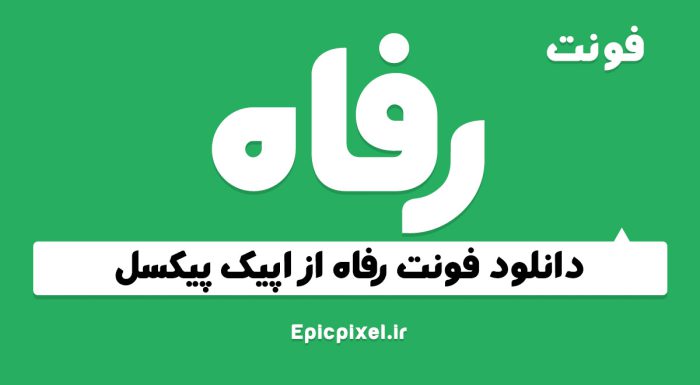
5 فونت رفاه فارسی
| ⭐ توضیحات | مجموعه ای کامل از فونت های رفاه و نسخه شبیه سازی شده بنام اپیک رفاه دانلود فونت اپیک رفاه با پشتیبانی از حروف فارسی / انگلیسی (لاتین) ، اعداد فارسی Fu Num و انگلیسی بهمراه نسخه وب |
فونت بانک رفاه یک فونت دکوراتیو برای طراحی لوگوتایپ و متن های طولانی
مقدمه
فونت رفاه یک فونت دکوراتیو است که برای طراحی لوگوتایپ و متن های طولانی مناسب است. این فونت توسط یک طراح حرفه ای و با سابقه فونت فارسی، طراحی شده است. فونت رفاه در سال 1402 به بازار عرضه شد و با استقبال خوب کاربران روبرو شد. این فونت دارای ویژگی های منحصر به فرد و جذابی است که در ادامه به آنها خواهیم پرداخت.
تعریف و معرفی فونت رفاه
فونت رفاه یک فونت دکوراتیو است که بر اساس الگوهای هندسی و ساده ساخته شده است. این فونت دارای حروف بزرگ و کوچک، اعداد، علائم نگارشی و نمادهای خاص است. این فونت با تمام قلم های لاتین سازگار است و می توان از آن برای نگارش متن های چند زبانه استفاده کرد. فونت رفاه برای طراحی لوگوتایپ، پلاکارد، بروشور، پوستر، کارت ویزیت، سربرگ، بنر، تقویم، سررسید و متن های آموزشی، هنری و تفریحی مناسب است.
اهداف و مزایای استفاده از فونت رفاه
اولین هدف ایجاد یک فونت دکوراتیو با کیفیت بالا و قیمت مناسب برای کاربران ایرانی و عربی است. دومین هدف ارائه یک فونت با ساختار و ترکیب حروف منحصر به فرد و جذاب است که برای طراحی لوگوتایپ و متن های طولانی مناسب باشد. سومین هدف پشتیبانی از سه زبان فارسی، عربی و انگلیسی با حروف لاتین سازگار است. چهارمین هدف دسته بندی و حالات مختلف فونت رفاه است که شامل نرمال، نرمال ایرانیک، بولد و ضخیم می باشد. پنجمین هدف سهولت استفاده از فونت رفاه در برنامه های مختلف است.
دانلوداستفاده از فونت رفاه چندین مزیت دارد. اولین مزیت زیبایی و جذابیت فونت رفاه است که باعث می شود مخاطب را به خود جذب کند. دومین مزیت خوانایی و روان بودن فونت رفاه است که باعث می شود مطالب را به راحتی بخوانید و درک کنید. سومین مزیت چند منظوره بودن فونت رفاه است که باعث می شود برای هر نوع طراحی و نگارش متن مناسب باشد. چهارمین مزیت چند زبانه بودن فونت رفاه است که باعث می شود برای نگارش متن های چند زبانه بدون نگرانی از تغییر قلم استفاده کنید.
ویژگی های فونت رفاه
در این بخش به بررسی ویژگی های فونت رفاه خواهیم پرداخت. این ویژگی ها شامل نحوه استفاده از فونت رفاه در برنامه های مختلف، ساختار و ترکیب حروف فونت رفاه، پشتیبانی از سه زبان فارسی، عربی و انگلیسی و دسته بندی و حالات مختلف فونت رفاه می باشند.
ساختار و ترکیب حروف فونت رفاه
فونت رفاه دارای ساختار و ترکیب حروف منحصر به فرد و جذاب است. این فونت بر اساس الگوهای هندسی و ساده ساخته شده است. حروف فونت رفاه دارای خطوط صاف و گوش دار هستند که باعث می شود شکل حروف به چشم بخورد. حروف فونت رفاه دارای ضخامت یکسان هستند که باعث می شود تعادل حروف حفظ شود. حروف فونت رفاه دارای فضای مناسب بین خود هستند که باعث می شود خوانایی حروف افزایش یابد.
دانلودبرخلاف بسیاری از قلم های دکوراتیو که دارای حروف پژمرده یا نامطابق با قوانین خط فارسی هستند، فونت رفاه دارای حروف مطابق با قوانین خط فارسی است. این فونت دارای حروف اصلی، حروف متصل، حروف متصل پایانی، حروف متصل اولیه، حروف متصل وسطی و حروف غیر متصل است. این فونت همچنین دارای حروف ترکیبی، حروف ترکیبی پایانی، حروف ترکیبی اولیه و حروف ترکیبی وسطی است. این فونت با رعایت قوانین خط فارسی، ترکیب حروف را به صورت زیبا و هماهنگ انجام می دهد.
پشتیبانی از سه زبان فارسی، عربی و انگلیسی
فونت رفاه یک فونت چند زبانه است که از سه زبان فارسی، عربی و انگلیسی پشتیبانی می کند. این فونت دارای حروف لاتین سازگار با حروف فارسی و عربی است. این فونت با رعایت قوانین خط فارسی و عربی، حروف را به صورت صحیح و مطابق با نحوه خواندن آنها نمایش می دهد. این فونت همچنین دارای علائم نگارشی و نمادهای خاص برای هر زبان است. برای مثال، این فونت دارای علامت سؤال، علامت تعجب، علامت نقطه چین، علامت کاما، علامت دو نقطه، علامت خط تیره، علامت پرانتز، علامت کروشه، علامت نقل قول، علامت درصد، علامت دلار، علامت یورو، علامت پوند، علامت چکیده و … برای هر زبان است.
دسته بندی و حالات مختلف فونت رفاه
فونت رفاه یک فونت با دسته بندی و حالات مختلف است. این فونت شامل چهار حالت مختلف است که هر کدام دارای ویژگی های خود هستند. این حالات عبارتند از:
حالت نرمال: این حالت حالت پایه و استاندارد فونت رفاه است. در این حالت حروف دارای ضخامت معمول و شکل هندسی هستند. این حالت برای متن های طولانی و معمول مناسب است.